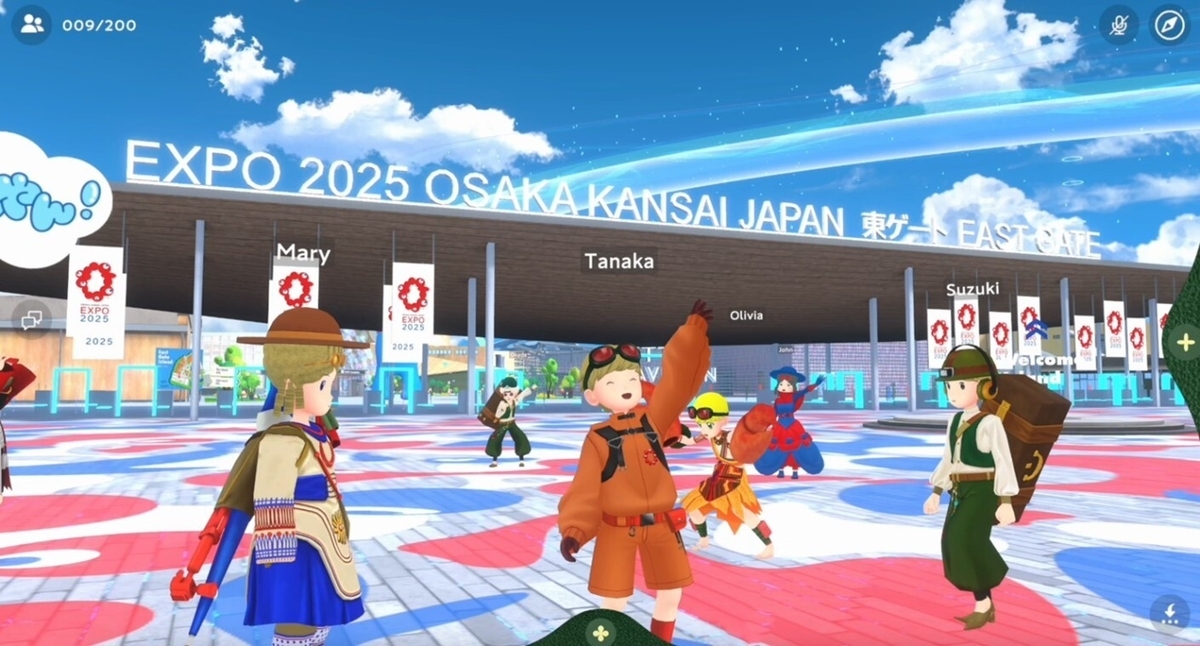
大阪・関西万博の世界をバーチャル空間で楽しめるアプリ「EXPO 2025 バーチャル万博 ~空飛ぶ夢洲~」にモリサワのフォントが採用
モリサワのフォントが、2025年日本国際博覧会の世界をバーチャル空間で楽しめるアプリとして、2025年4月3日(木)よりダウンロードが可能となった「EXPO 2025 バーチャル万博 ~空飛ぶ夢洲~」アプリ(以下、バーチャル万博アプリ)に採用されたことを2025年4月3日に発表した。
バーチャル万博アプリでは、アバターとなって空飛ぶ夢洲をコンセプトにした大阪・関西万博のバーチャル会場に入り込み、実際の建物が再現されたパビリオン・イベント施設を巡りながら、各出展者が展開するバーチャルならではの展示やイベントを楽しむことができ、実際の大阪・関西万博の来場者がこの専用アプリを使うことによって、会場に行く前の事前学習ができたり、ARコンテンツを体験することができる。
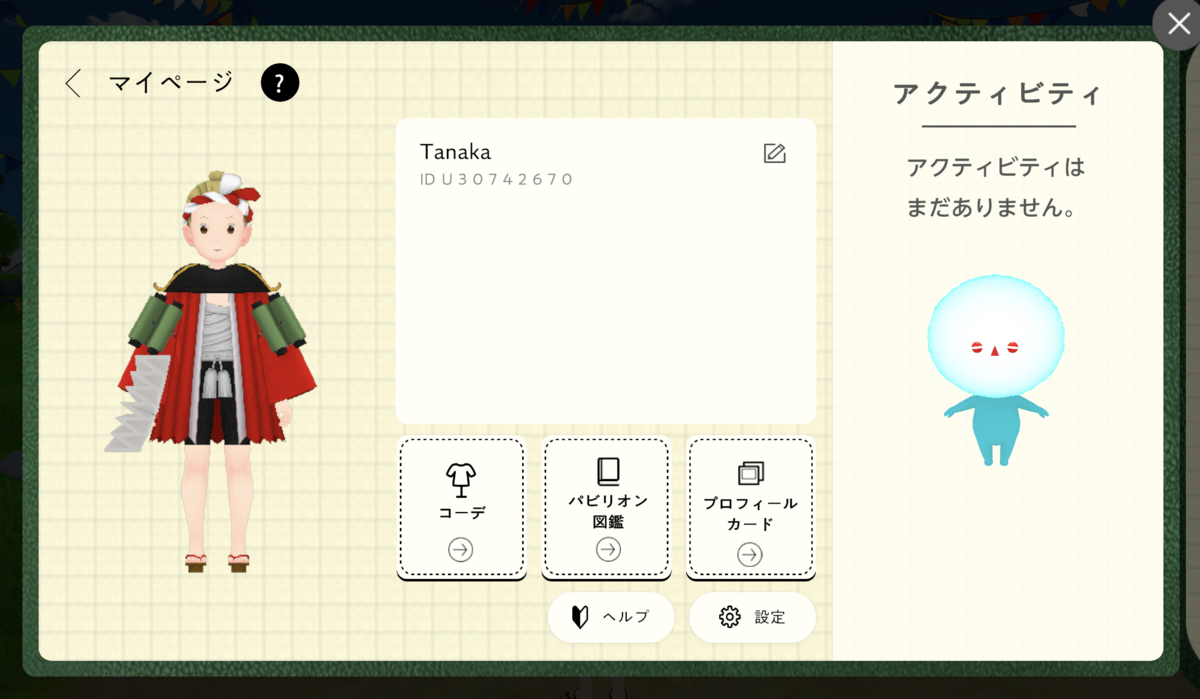
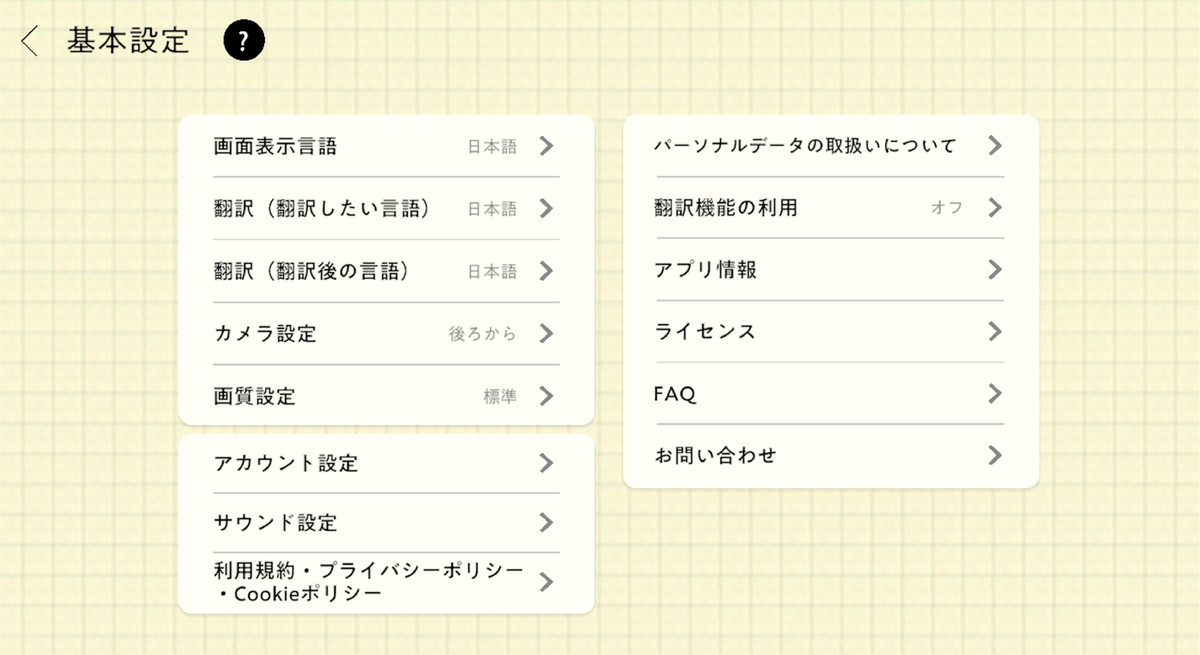
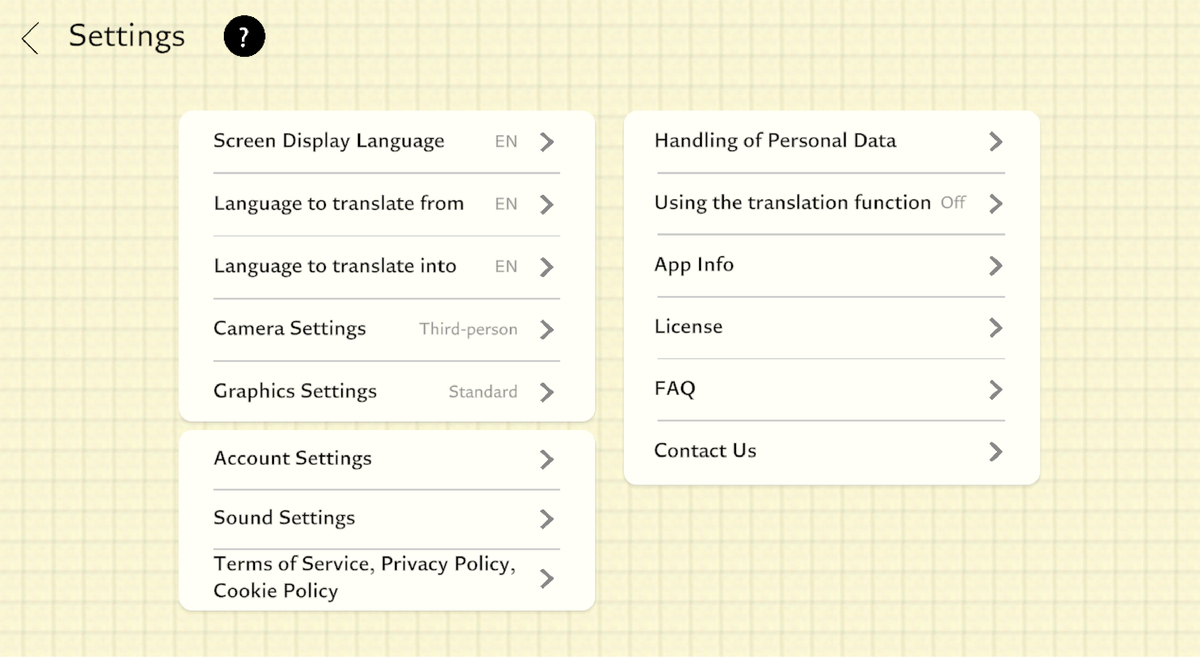
アプリのUIに採用されたフォントは、温もりのあるデザインが人気のA1ゴシックのほか、欧文スーパーファミリーのRole Sans Text Pro、日本語表記に使用するUD新ゴNT、UD新ゴ ハングル、UD新ゴ 簡体字に加え、151言語をカバーするClarimo UD PEとアラビア文字のClarimo UD Arabicとなる。
Clarimo UDシリーズは、可読性を重視したシンプルで汎用性の高いサンセリフ書体で、「UD新ゴ」シリーズとも親和性のあるデザインのフォント。